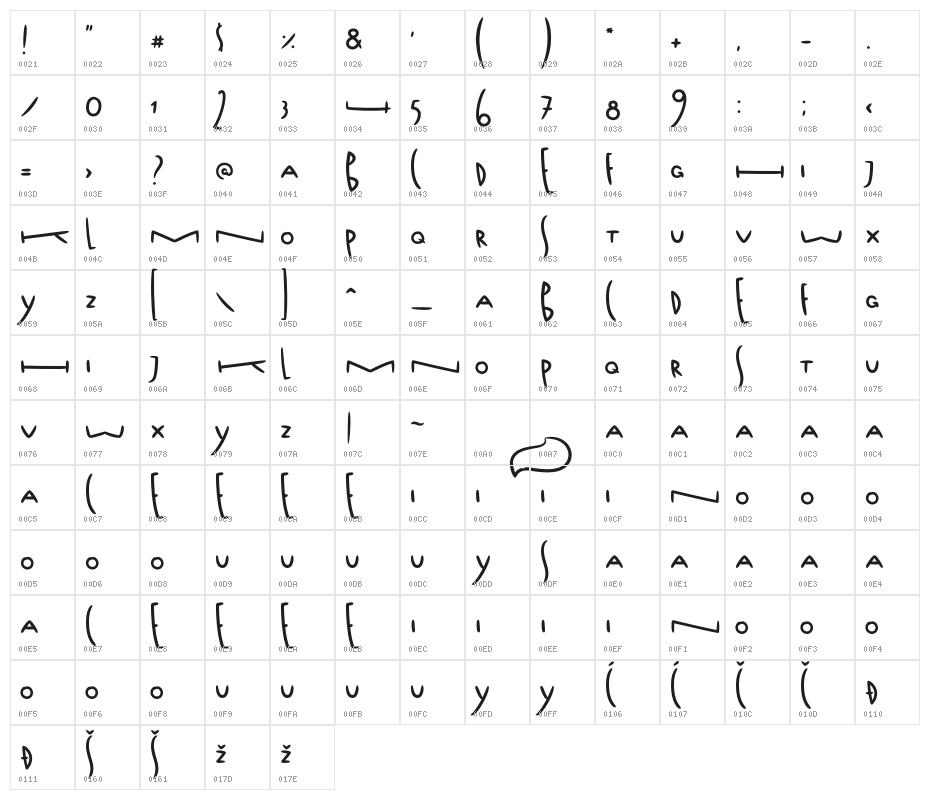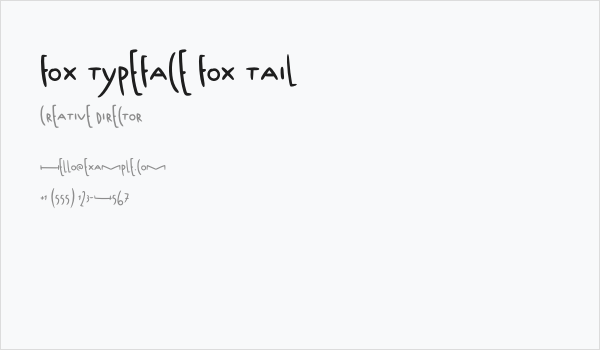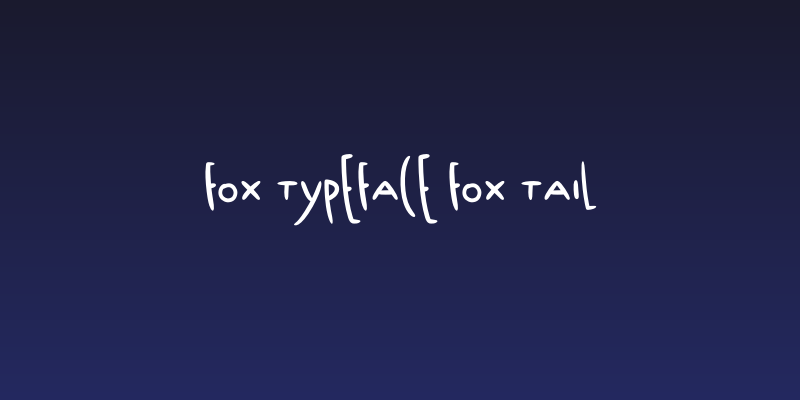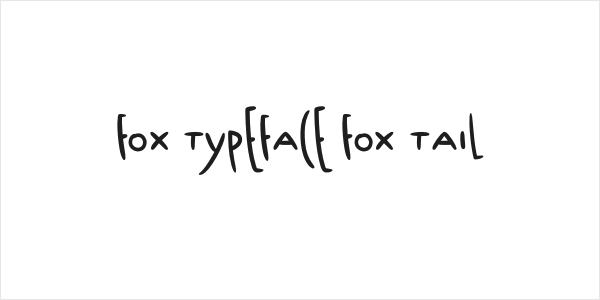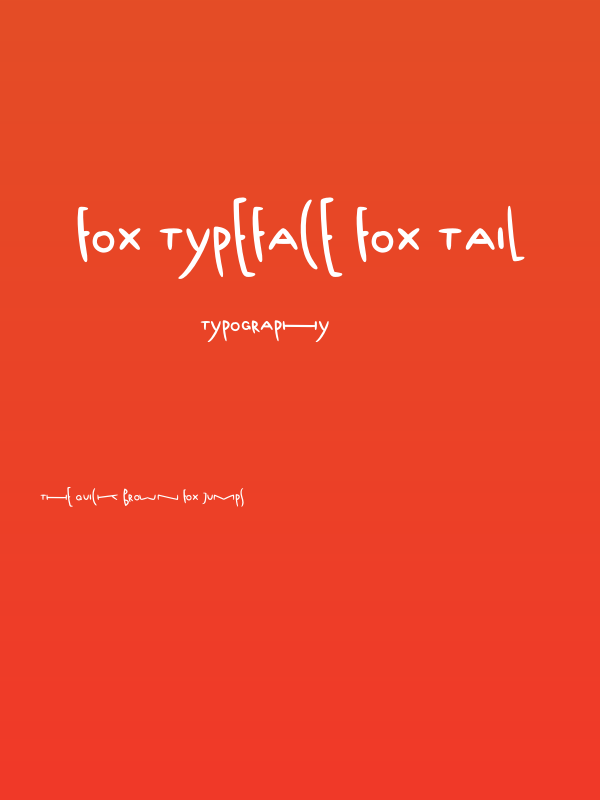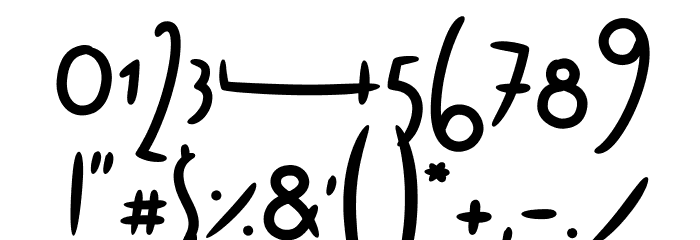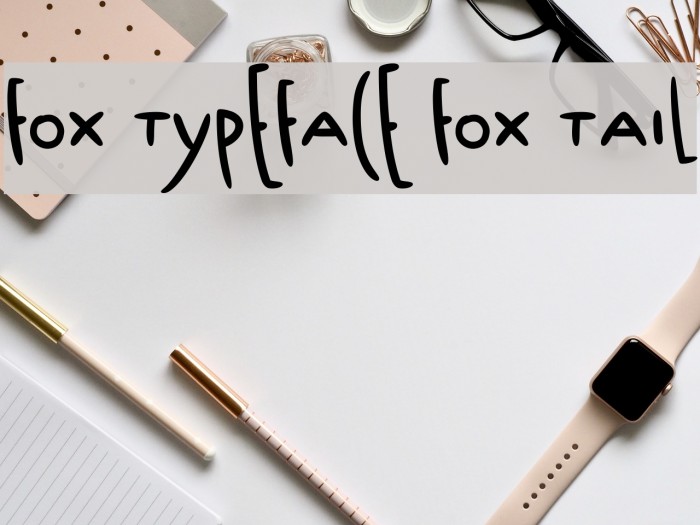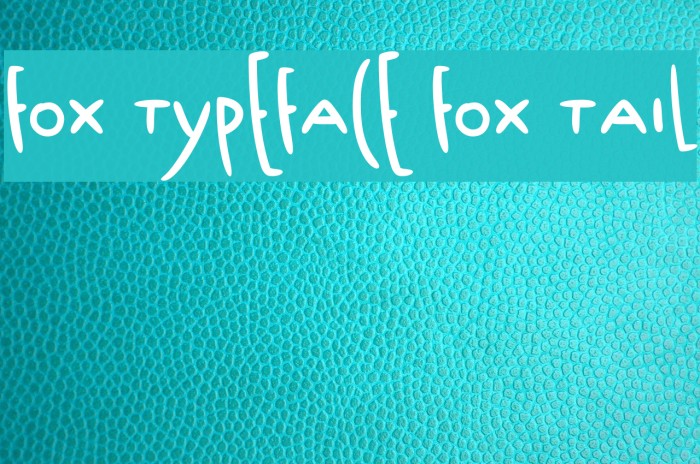
Fox Typeface Fox Tail Font
| Projets proposés | Ideal for children's books, playful branding, greeting cards, and creative posters. |
Fox Typeface Fox Tail